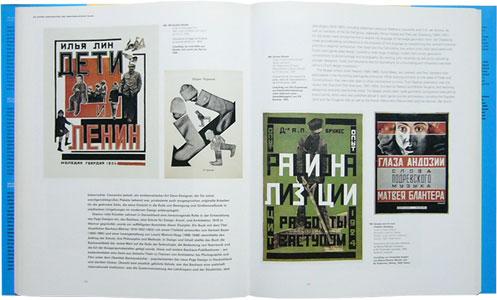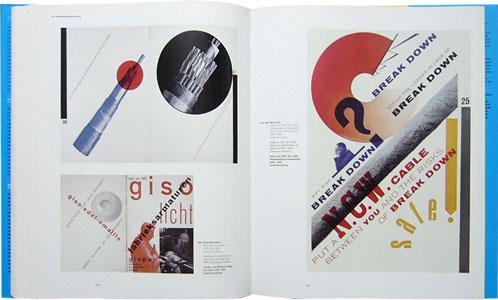
Avant-Garde Page Design 1900–1950
Jaroslav Andel beleuchtet in seinem Buch die Entwicklung der Avantgarde-Typografie zu Beginn des 20. Jahrhunderts. Über diverse Vorläufer und Pioniere des typografischen Experiments im 18. und 19. Jahrhundert, spannt er einen Bogen zu den typografischen Arbeiten der Kubisten, Expressionisten, Futuristen, Dadaisten, Konstruktivisten, De Stijl, Vertretern der Neuen Typografie, u.a. Parallel werden die wechselseitigen Einflüsse und Beziehungen zwischen der experimentellen Typografie und der bildenden Kunst, Architektur, Film und Fotografie beleuchtet. Entgegen des Titels endet Andel bereits Mitte der 1930er mit seinen Ausführungen; einen Ausblick auf folgende (experimentelle) Typografie-Generationen gibt er nicht.